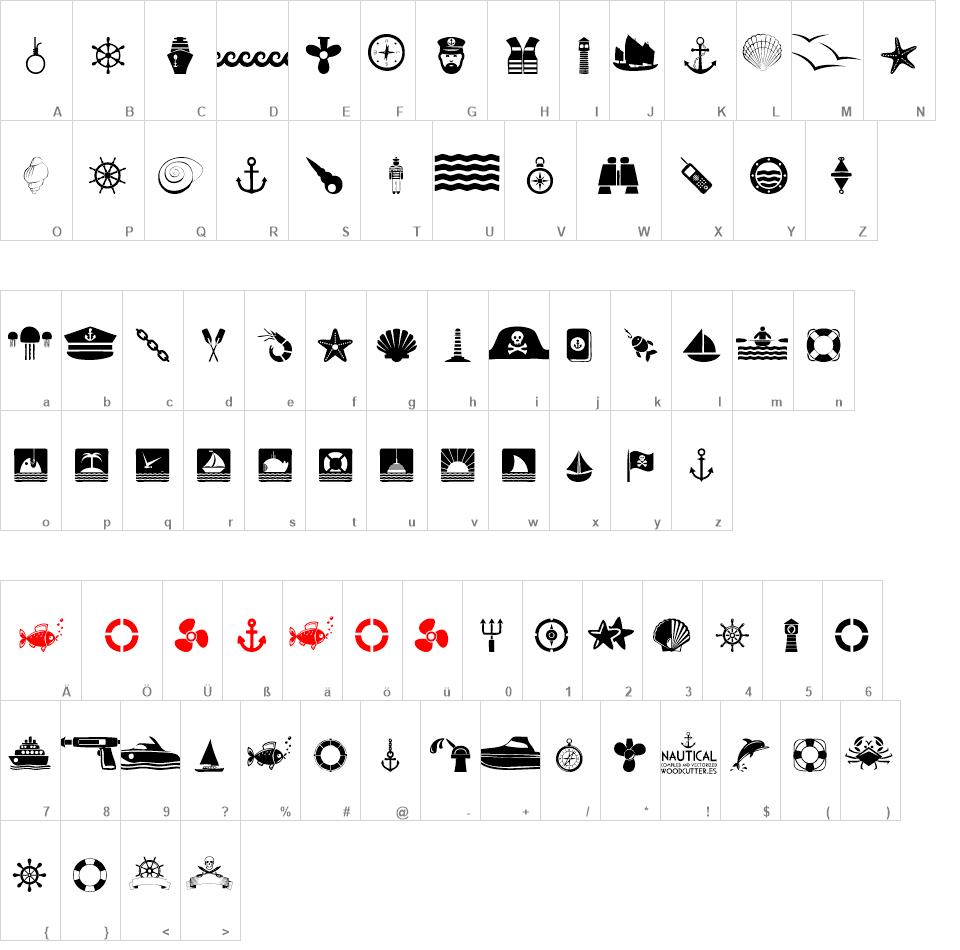
Nautical
Nautical font
Nautische, marine Schriftarten. Anker Schriftart, maritime Schriftart, Eisen Schriftart, Kompass Schriftart, Ruder Schriftart, Pirat Schriftart.